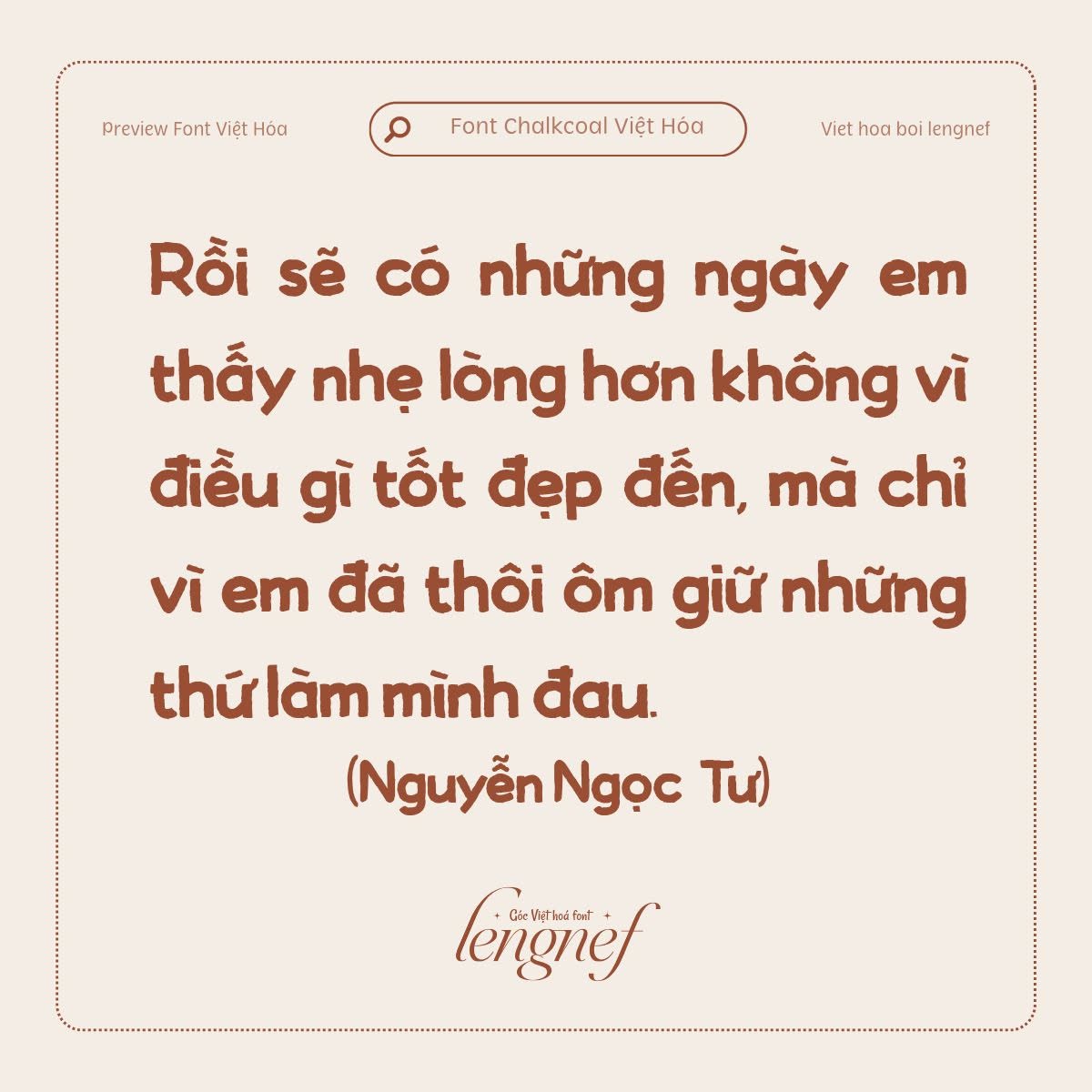
Việt hóa theo yêu cầu 12 || LF Chalkcoal
- Tác giả: Letterey
- Việt hóa: lengnef
Chalkcoal là phông chữ viết tay, nét đậm, kiểu dễ thương. Phông chữ này mang phong cách vui tươi và tinh nghịch gợi nhớ đến chữ viết bằng phấn trên bảng đen. Các ký tự không đều tạo nên vẻ ngoài tự nhiên, thêm chút ngẫu hứng tạo ấn tượng thị giác mạnh mẽ. Phông chữ này hoàn hảo cho các dự án nhằm truyền tải sự sáng tạo và thoải mái.